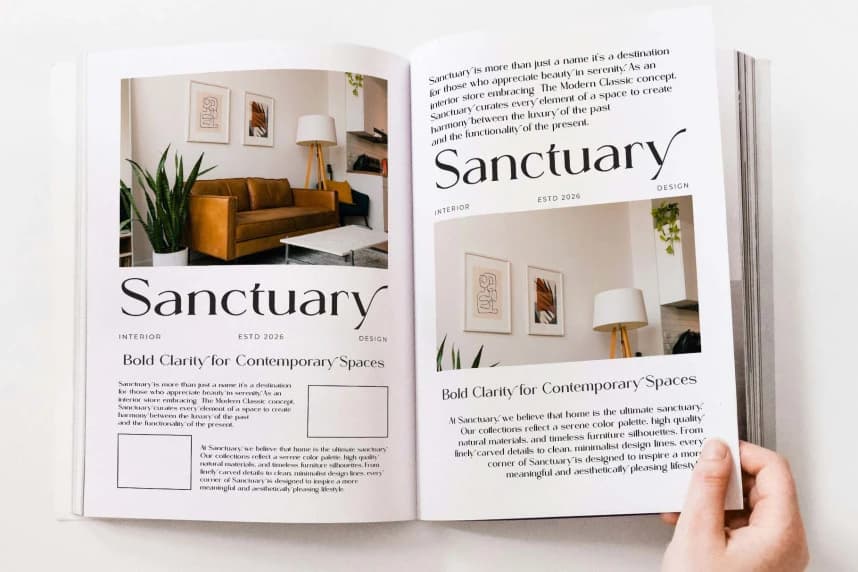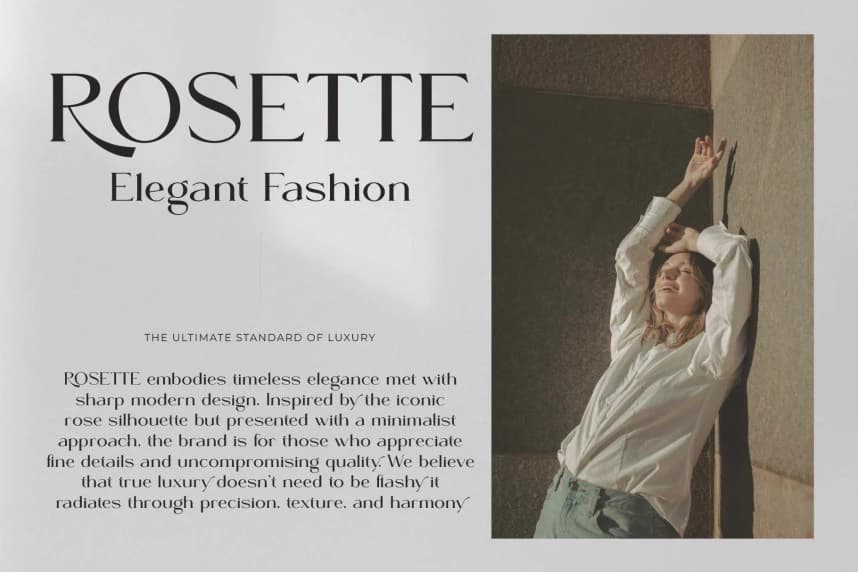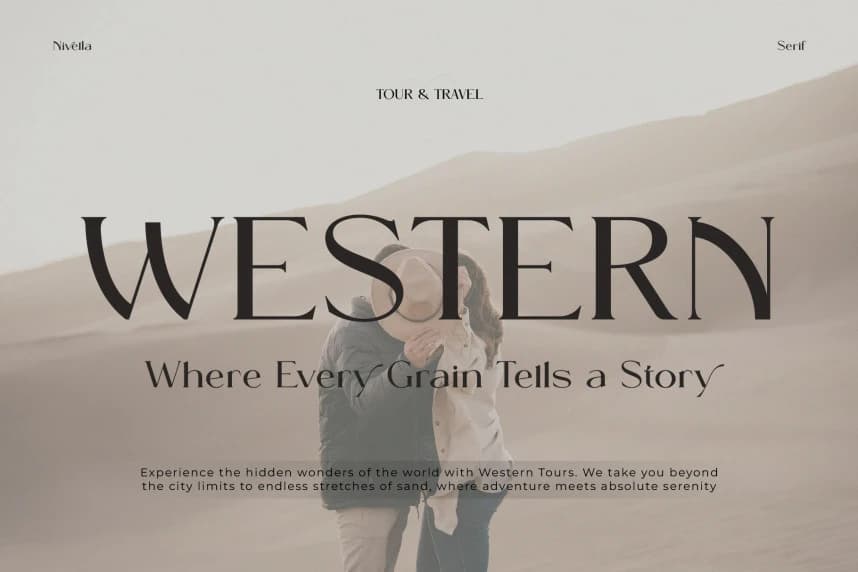
Nivella Font
Nivella Font, modern bir serif yazı tipidir. Bu yazı tipi, geleneksel serif yapısı ile modern minimalist tarza mükemmel bir denge kurar. Yüksek kontrastlı çizgilere ve temiz, keskin uçlara sahip olan bu yazı tipi, parlak ve profesyonel bir enerji yayar.
Nivella Font, modern bir serif yazı tipidir. Bu yazı tipi, geleneksel serif yapısı ile modern minimalist tarza arasında mükemmel bir denge kurar. Yüksek kontrastlı çizgilere ve temiz, keskin uçlara sahiptir; bu öğeler cilalı, profesyonel bir enerji yayar.